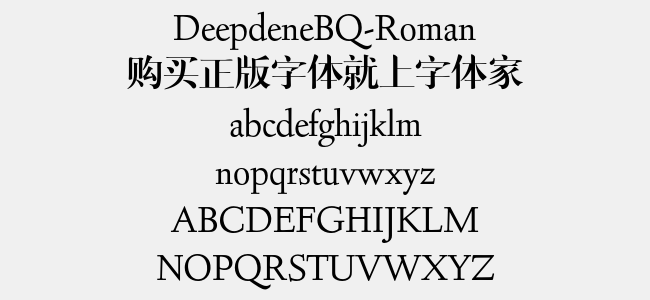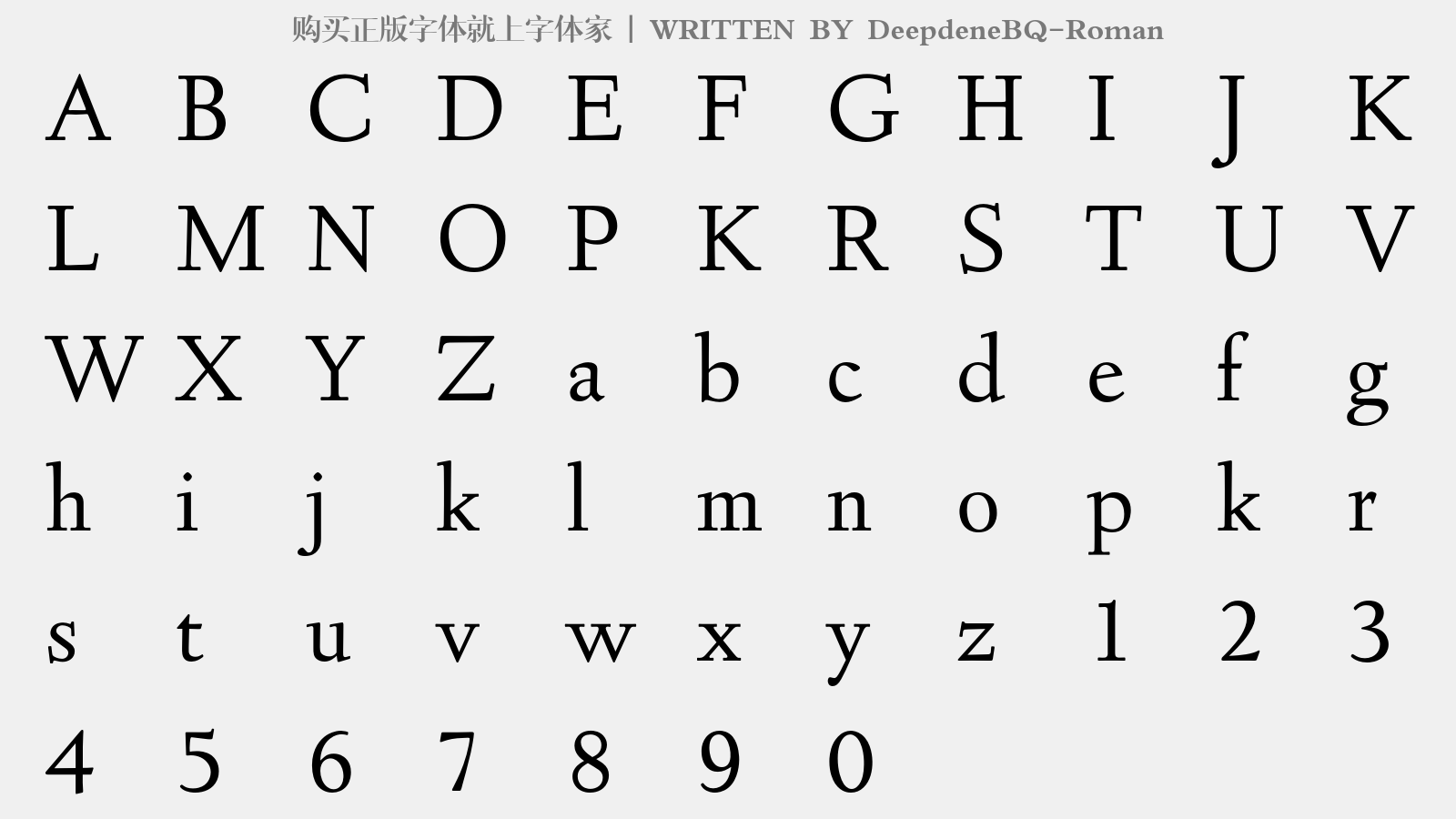
DeepdeneBQ-Roman
字体作者:现代字体
字体名称:DeepdeneBQ-Roman
字体字数:26个英文大小写字母及和阿拉伯数字
书体类型:英文类
DeepdeneBQ-Roman
该字体是一款个性独特的英文字体,非常适合创意类的PS字体,英文广告设计载体上使用,在设计中选择这款字体应用的话,会起到非常理想的效果。